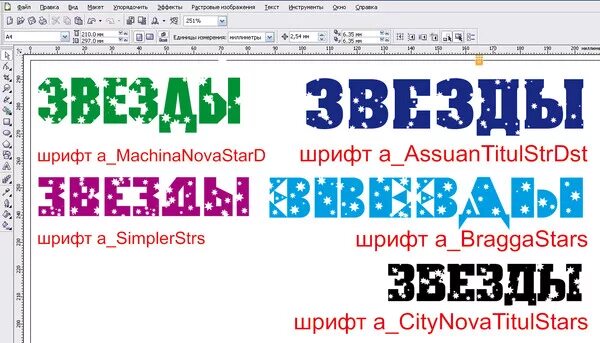
Шрифт со звездами. Звездный шрифт. Шрифт из звезд. Шрифт со звездочкамиЗвездный шрифт. Шрифт со звездами. Шрифт из звездШрифт со звездами. Шрифт со звездочками русскийШрифт со звездочками. Шрифт со звездами. Русские буквы из звезд. Шрифт из звездЗвездный шрифт. Шрифт со звездами. Шрифт из звезд. Шрифт из звездочекЗвездный шрифт. Шрифт со звездами. Шрифт из звезд. Шрифт со звездами кириллицаЗвездный шрифт. Шрифт со звездами. Шрифт из звезд. Шрифт Звёздное небоШрифт со звездочками. Шрифт со звездочками русскийШрифт со звездами. Звездный шрифт. Шрифт со звездочкамиШрифт со звездами. Шрифт со звездочками. Шрифт из звездШрифт со звездами. Звездный шрифт. Шрифт из звезд. Шрифт со звездами кириллицаЗвездный шрифт. Шрифт со звездами. Шрифт из звезд. Billions шрифтЗвездный шрифт. Шрифт со звездами. Шрифт из звезд. Шрифт со звездочками русский. Шрифт со звездочкамиШрифт со звездами. Звездный шрифт. Буквы со звездами Пинтерест для оформленияШрифт со звездами. Звездный шрифт. Алфавит прописные буквыШрифт со звездами. Шрифт со звездочками русскийШрифт со звездами. Звездный шрифт. Шрифт со звездочкамиStrong fontШрифт со звездочками. Шрифт со звездочками русский. Звёздочка красивый шрифтШрифт со звездами. Звездный шрифт. Шрифт из звезд. Звездный шрифт русскийШрифт со звездочками. Шрифт со звездочками русский. Звездный шрифт кириллицаШрифт Star. Шрифт со звездами. Шрифт из звезд. PARATYPE шрифтШрифт со звездами. Шрифт из звезд. Шрифт со звездочкамиШрифт со звездами. Шрифт звезды для фотошопа. Шрифт из звезд. Звезда шрифт символRandom шрифт. Шрифт старых мемовШрифт со звездами. Звездный шрифт. Шрифт из звезд. Шрифт звезды для фотошопаШрифт со звездами. Шрифт Aster. Aster font. Rione Stars fontШрифт со звездочками. Символьные шрифты звездочки. Шрифт со звездами. Звезда шрифт символMoon шрифт. Шрифт Луна. Moon font. A shrift with Moon logoШрифт со звездами. Star надпись. Шрифт из звезд. Звездный шрифтШрифт со звездочками. Шрифт со звездочками русский. Дизайнерский шрифт со звездочкамиШрифт со звездами. Символьные шрифты звездочки. Шрифт со звездочками. Шрифт из звездШрифт со звездами. Текст со звездами шрифт. Its Full of StarsЗвездный шрифт. Шрифт со звездами. Шрифт со звездами кириллицаШрифт со звездочками. Шрифт со звездами. Символьные шрифты звездочки. Шрифт звезды для фотошопаЗвездный шрифт. Шрифт со звездами. Шрифт звезды для фотошопаКвадратный шрифт. Квадратный шрифт русский. Угловатый шрифт. Необычные шрифтыШрифт со звездами. Шрифт красная звездаШрифт из звездочек. Шрифт со звездами. Шрифт буквы из звезд. Шрифт звезды для фотошопаШрифт со звездами. Шрифт звезды для фотошопа. Шрифт Revenge. Star fontШрифт со звездами. Шрифт звезды для оформления. Шрифт звезда 5 конечнаяШрифт со звездами. Звезда шрифт символЗвездный шрифт. Шрифт из звезд. Шрифт звезды для фотошопа. Шрифт из звезд русскийСнежный шрифт. Шрифт со снегом. Декоративный шрифт. Снежный шрифт русскийШтриховой шрифт. Шрифт со штриховкой. Штрихованный шрифт кириллица. Заштрихованный шрифт кириллицаКрасивые синие буквы. Буквы для оформления. Объемные цветные буквы. Красивые объемные буквыШрифт для хоккейной формы кириллица. Рубленный шрифт. Квадратный шрифт. Рубленый шрифт кириллицаPer aspera ad Astra тату. Через тернии к звездам надпись. Тату через тернии к звездам эскизы. Звезда эскизШрифт цирк. Шрифт в стиле цирк. Шрифт цирк русский. Цирковой шрифт русскийШрифты русские дизайнерские. Геометрические дизайнерские шрифты. Векторный шрифт. Дизайнер шрифтовБуквы стразами. Красивые буквы из страз. Буквы стразами трафарет. Надпись стразамиЗимний шрифт. Зима шрифт. Шрифт со снегом. Шрифт снежинкиШрифт стразы. Буквы стразами. Шрифт буквы в для стразами. Бриллиантовые буквы для фотошопаШрифт со снегом. Шрифт со звездами. Лунный свет шрифт на русском языке. Дутый шрифт как снегАлфавит и буквы. Красивые буквы алфавита. Детские буквы. Объемный алфавитОбъемный шрифт русский. Шрифт с обводкой. Объемный шрифт с тенью. Английский алфавит с объемными буквамиШрифт из трещин. Заводской шрифт. Ломаный шрифт. Шрифт с трещинами русскийАльтернативные шрифты. Font for website. Huawei шрифт. Comic Sans Şerif font downloadШрифт со звездочками русский. Barboskins Akzident Regular font. Kasia Regular font. Kindah Regular fontNew шрифт. Нью зелек шрифт. Скошенный шрифт. Шрифт со скошенными угламиБуквы из страз. Шрифт стразы. Шрифт буквы в для стразами. Буквы стразами русскиеНовогодний шрифт. Новогодний шрифт русский. Красивый новогодний шрифт. Зимний шрифтДекоративный шрифт. Шрифт в виде нот. Шрифт штрихами. Декоративный шрифт с линиямиШрифт трафаретный русский. Советский трафаретный шрифт. Шрифт под трафарет. Шрифт для лазераЛето шрифты приложение. Шрифт Stepa. Шрифт Московская область. Шрифт на хозблокеШрифт спираль. Шрифты в математическом стиле. Необычные математические шрифты. Шрифт со звездочкамиПрикольные шрифты на русском. Забавный шрифт русский. Смешной шрифт. Веселый шрифт кириллицаКвадратный шрифт. Угловатый шрифт. Советский рубленый шрифт. Прямоугольный шрифтДизайнерские шрифты. Шрифты надписи. Широкий дизайнерский шрифт. Сложные шрифтыБуквы из звезд. Русские буквы из звезд. Созвездие в виде буквы у. Алфавит звездыШрифт со смещением. Шрифт со сдвигом. Смещенный шрифт. Шрифт сдвиг буквыШрифт со звездами. Красные звездочки в ряд. Star things. Звезда шрифт шаблон технические 3 ммРубленый шрифт. Рубленый шрифт без засечек. Широкий рубленый шрифт. Шрифты кириллицаКвадратный шрифт. Квадратный шрифт с закругленными углами. Прямоугольный шрифт. Угловатый шрифтОкруглый шрифт. Закругленные шрифты. Круглый шрифт. Необычные шрифты русскиеОкруглый шрифт. Буквы в стиле пузырей. Модные округлые шрифты. Шрифт толстый округлый кириллицаИгровой шрифт. Оригинальные шрифты для логотипа. Шрифты для игр. Шрифт в военном стилеТрафаретный шрифт. Шрифт для трафарета. Шрифт под трафарет. Stencil шрифтШрифт перфорация. Готический шрифт кириллица. Готический шрифт русский. Угловатый шрифтШрифт букв. Декоративный шрифт. Шрифты на русском. Шрифт для плаката